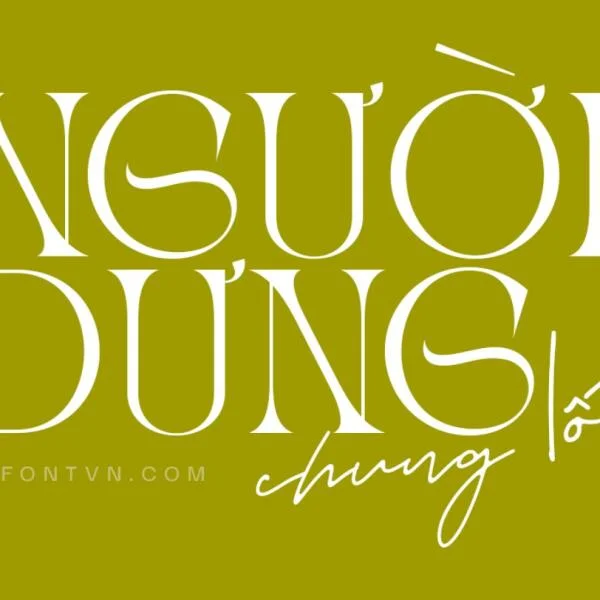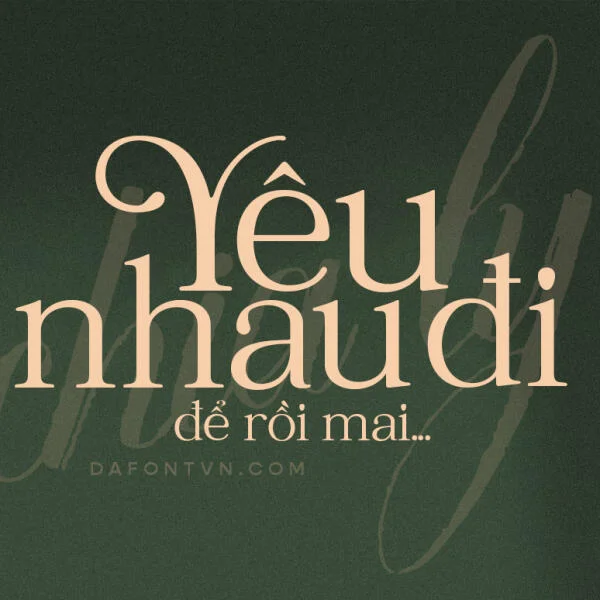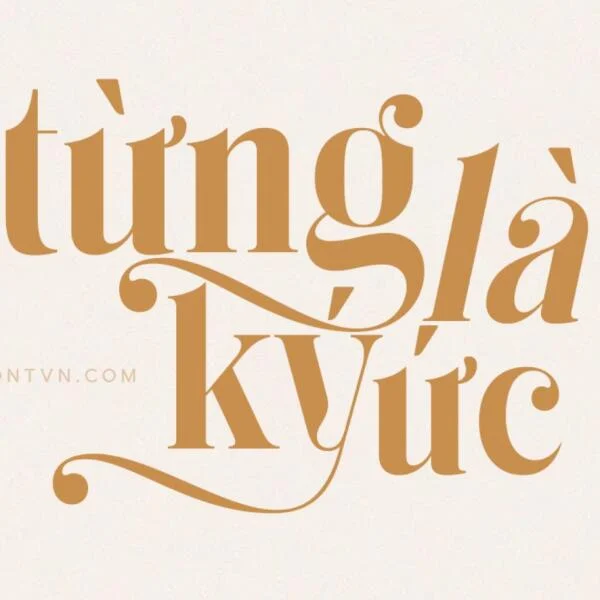
TẢI FONT MAUNG VIỆT HÓA – PHÔNG CHỮ HIỆN ĐẠI, ĐỘC ĐÁO
IoTStartUp chia sẻ tới bạn đọc Font Maung Việt hóa - một font chữ độc đáo, mang tính hiện đại sử dụng phù hợp trong mọi thiết kế. Tải về phông chữ sáng tạo này ở cuối bài viết nhé!
Font Maung - 1 kiểu serif hiện đại, mới mẻ
Maung Font được thiết kế ấn tượng và đặc biệt hơn font chữ còn có thêm các chữ ghép và các chữ xen kẽ có thiết kế uốn lượn mềm mại, độc đáo giúp tăng thêm nổi bật cho các tác phẩm của bạn.
Đặc biệt, khi tải bộ phông chữ Maung Tiếng Việt đầy đủ sẽ có thêm nhiều chữ ghép cùng các chữ xen kẽ thiết kế uốn lượn tạo cảm giác mềm mại tăng thêm phần nổi bật cho sản phẩm thiết kế
Có thể nói rằng font Maung sử dụng cho mọi loại thiết kế, trong đó không thể không kể đến thiết kế quảng cáo, thiết kế thiệp mời, xây dựng thương hiệu hay thiết kế bìa sách, tạp chí hoặc typography,…Qua đó bạn cũng có thể kết hợp giữa font Maung cùng nhiều font script khác tạo điểm nhấn cho thiết kế của bạn nhé.
Font Maung Việt hóa Preview 1
Mẫu 1
Font Maung Việt hóa Preview 2
Mẫu 2
Font Maung Việt hóa Preview 3
Mẫu 3
Font được việt hóa đầy đủ, kerning, features, chỉnh sửa, tối ưu và mã hóa PUA để bạn có thể sử dụng dễ dàng trên bất kỳ phần mềm thiết kế nào và đừng quên sử dụng bảng glyph để có những kiểu chữ thay thế xịn xò hơn nhé.
Font Maung Việt hóa Preview 5
Chi tiết 1
Font Maung Việt hóa Preview 6
Chi tiết 2